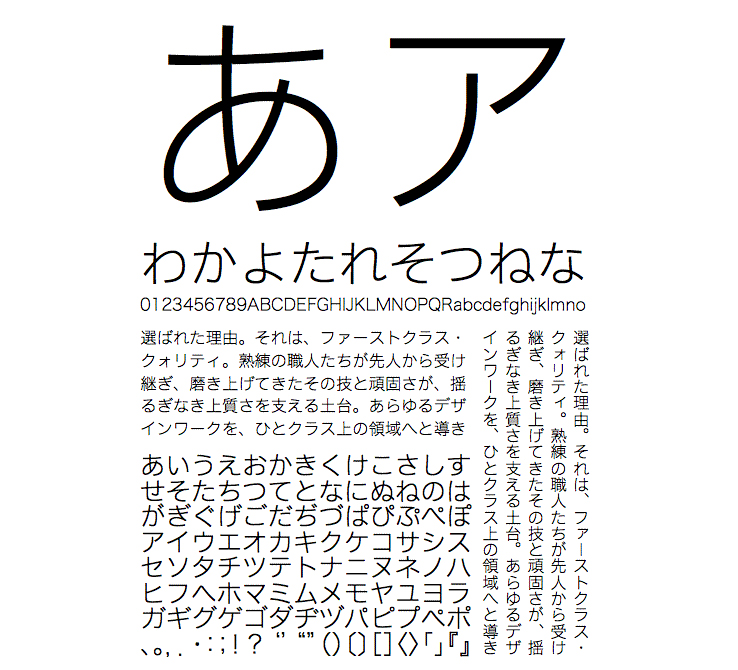
仮名・英数字グリフのみ収容
※本商品は仮名書体です。ギャラリーの見本に含まれる漢字はヒラギノ角ゴを使用しています。
【ヒラギノ角ゴAD仮名】「ヒラギノ角ゴ」と組み合わせ、広告の見出しから雑誌や広報誌、テロップやコーポレートフォントなど幅広く利用することが可能な仮名書体です。字面の大きさを同一ウエイト内でほぼ一定にしたため、横組みでも縦組みでも文章のラインが整った印象の組版になるのが特徴です。